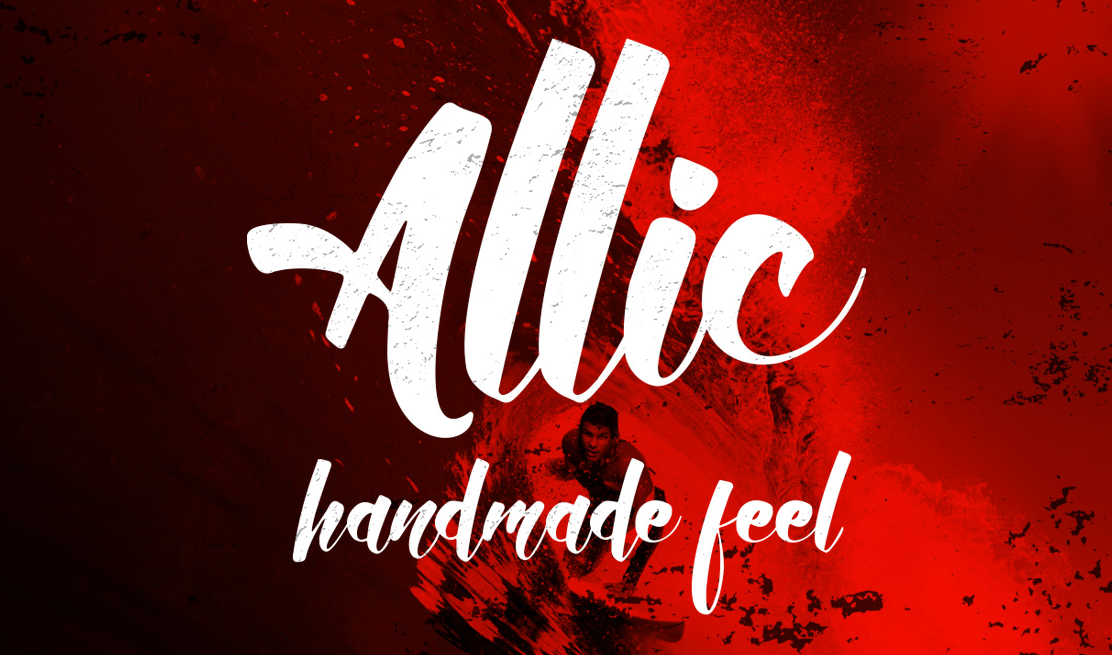
Allic Script Font – Download Grátis
A Allic Script Font é uma escolha incrível para quem procura uma fonte script moderna e vibrante. Seu estilo bold e fresco a tornam ideal tanto para cartões de aniversário e convites de casamento quanto para marca pessoal, papelaria, design de blogs, arte customizada, selos personalizados ou qualquer outra necessidade de design. Esta fonte brilha especialmente em textos chamativos e elegantes, criando um tom sofisticado e atraente sem ser excessivamente formal. Seja você designer gráfico profissional ou iniciante, a Allic Script Font é uma opção segura para levar seu trabalho à próxima grande dimensão.